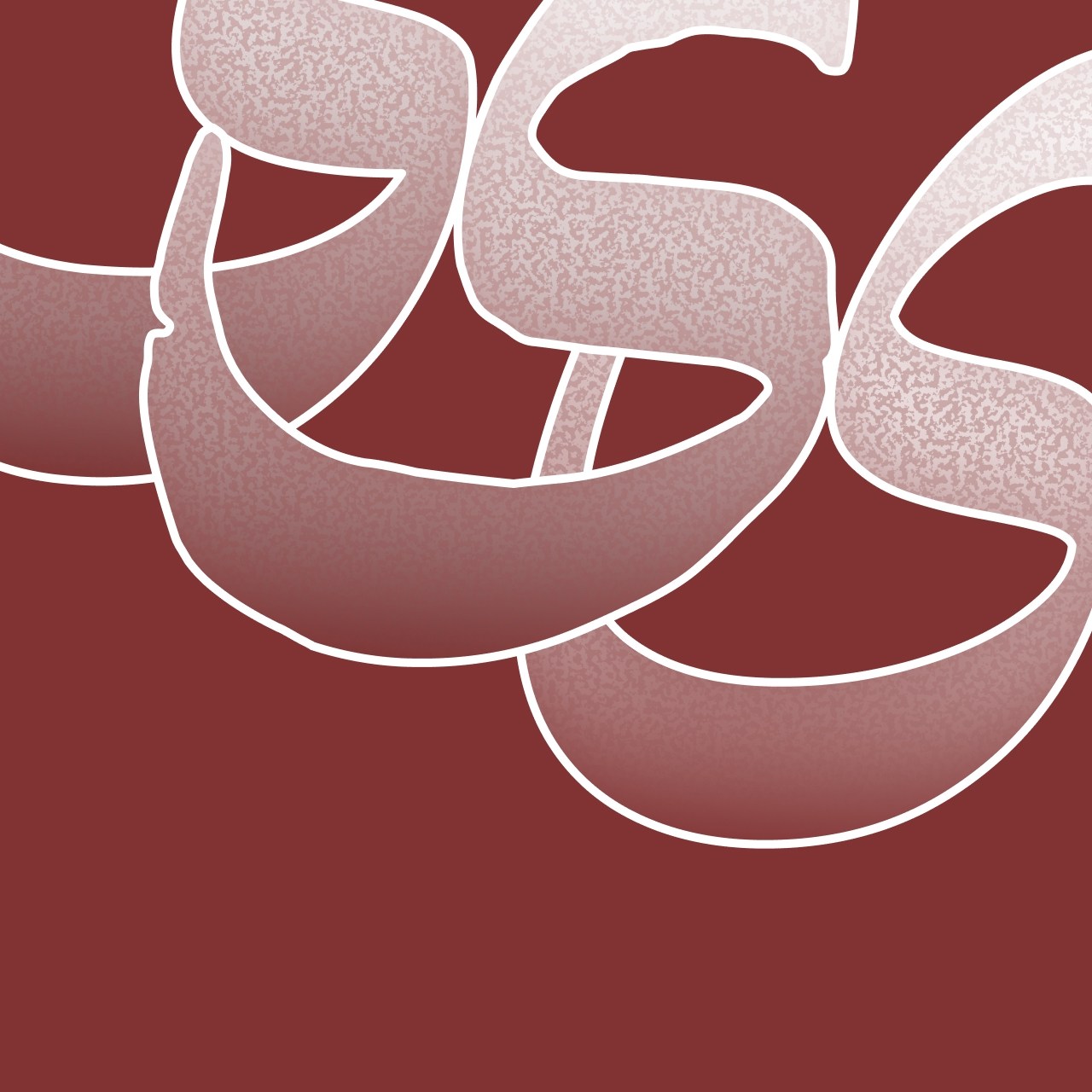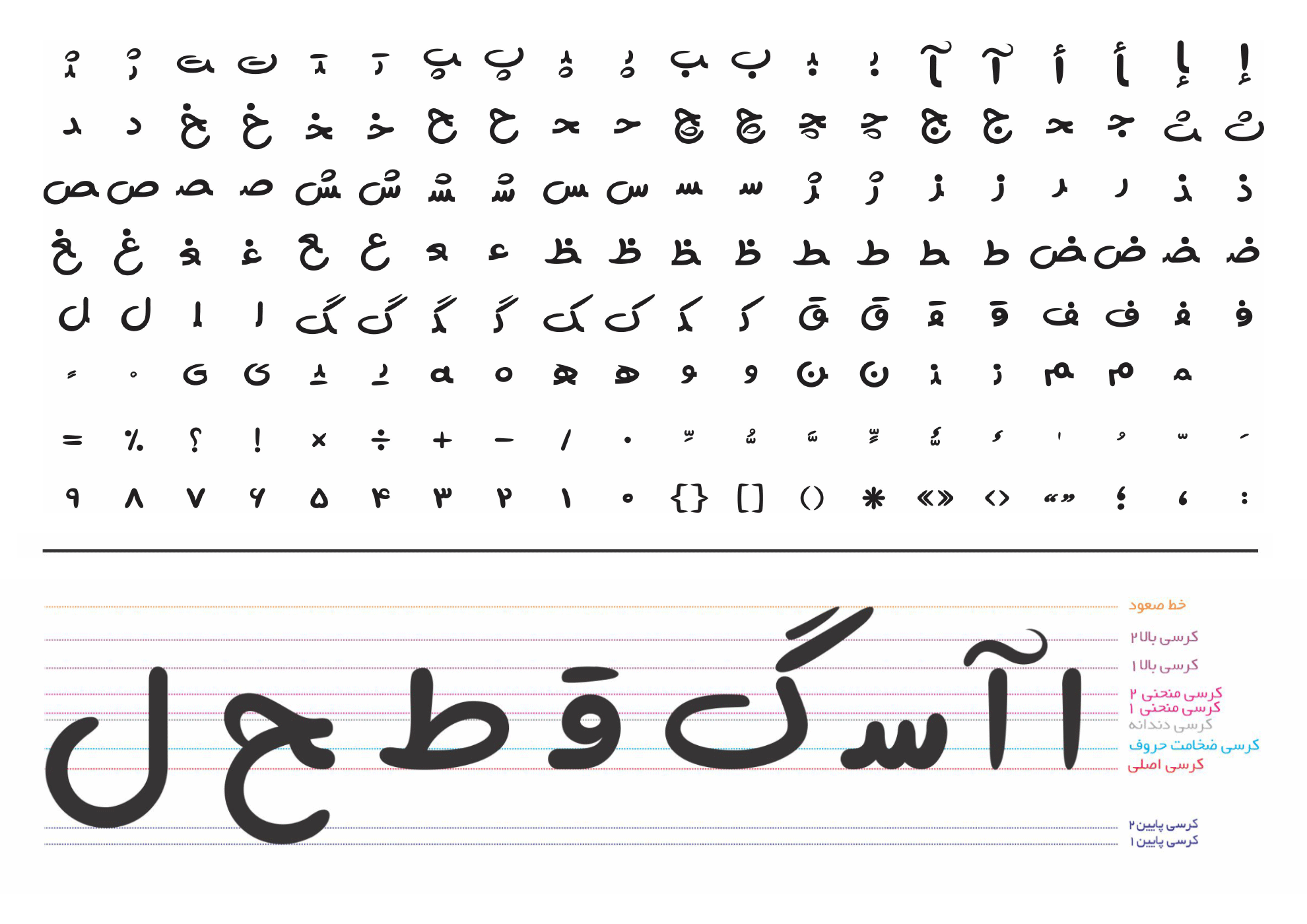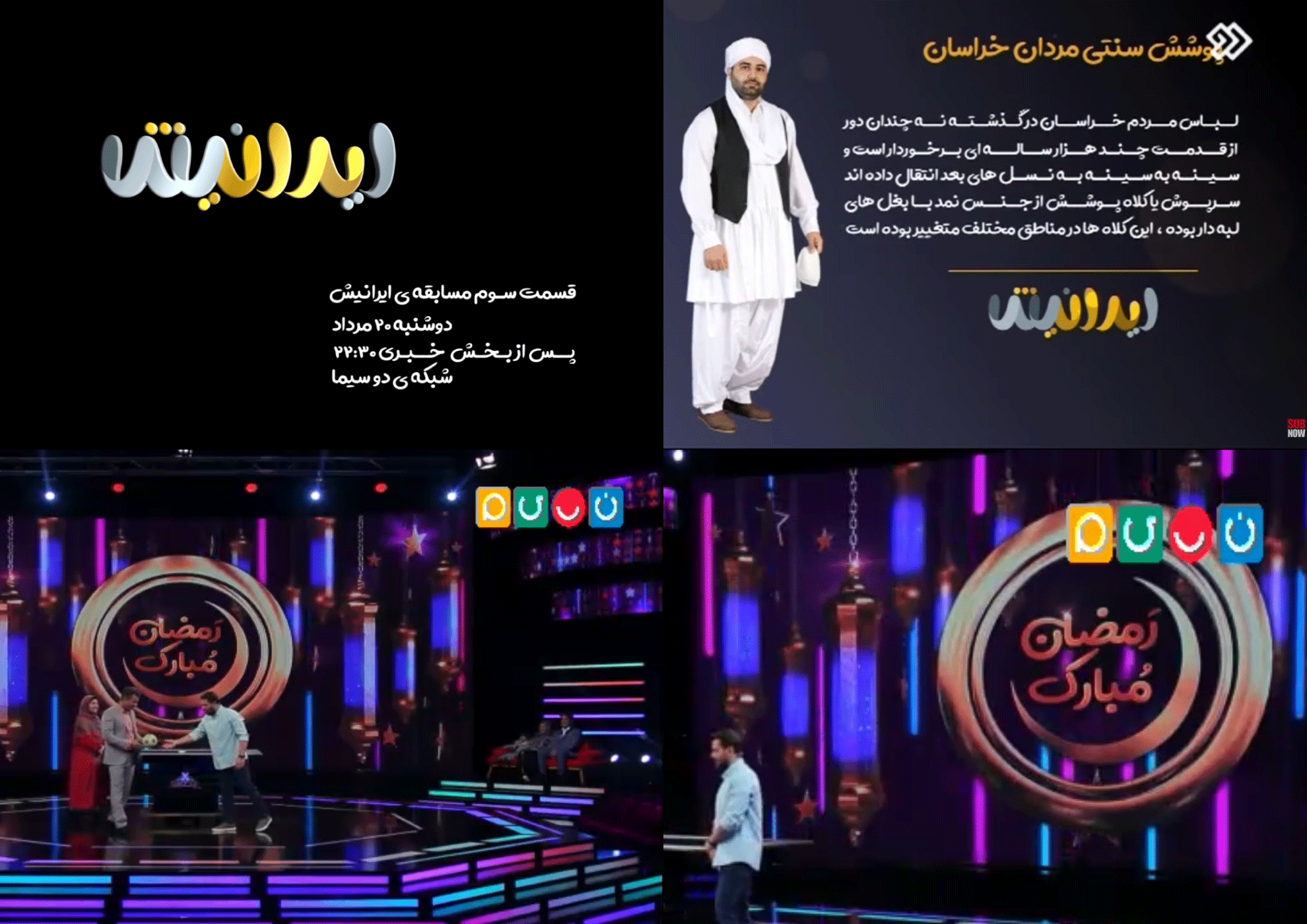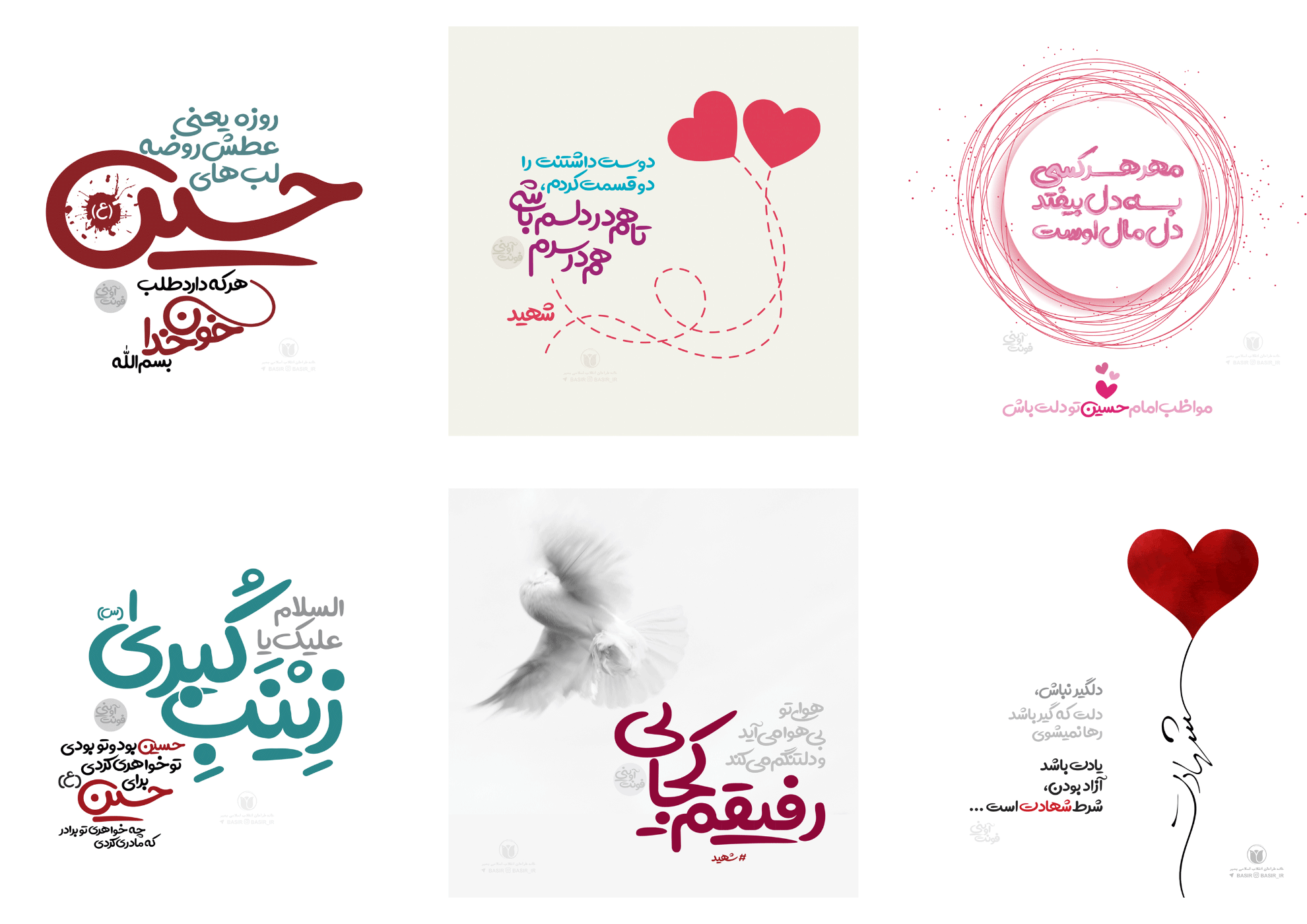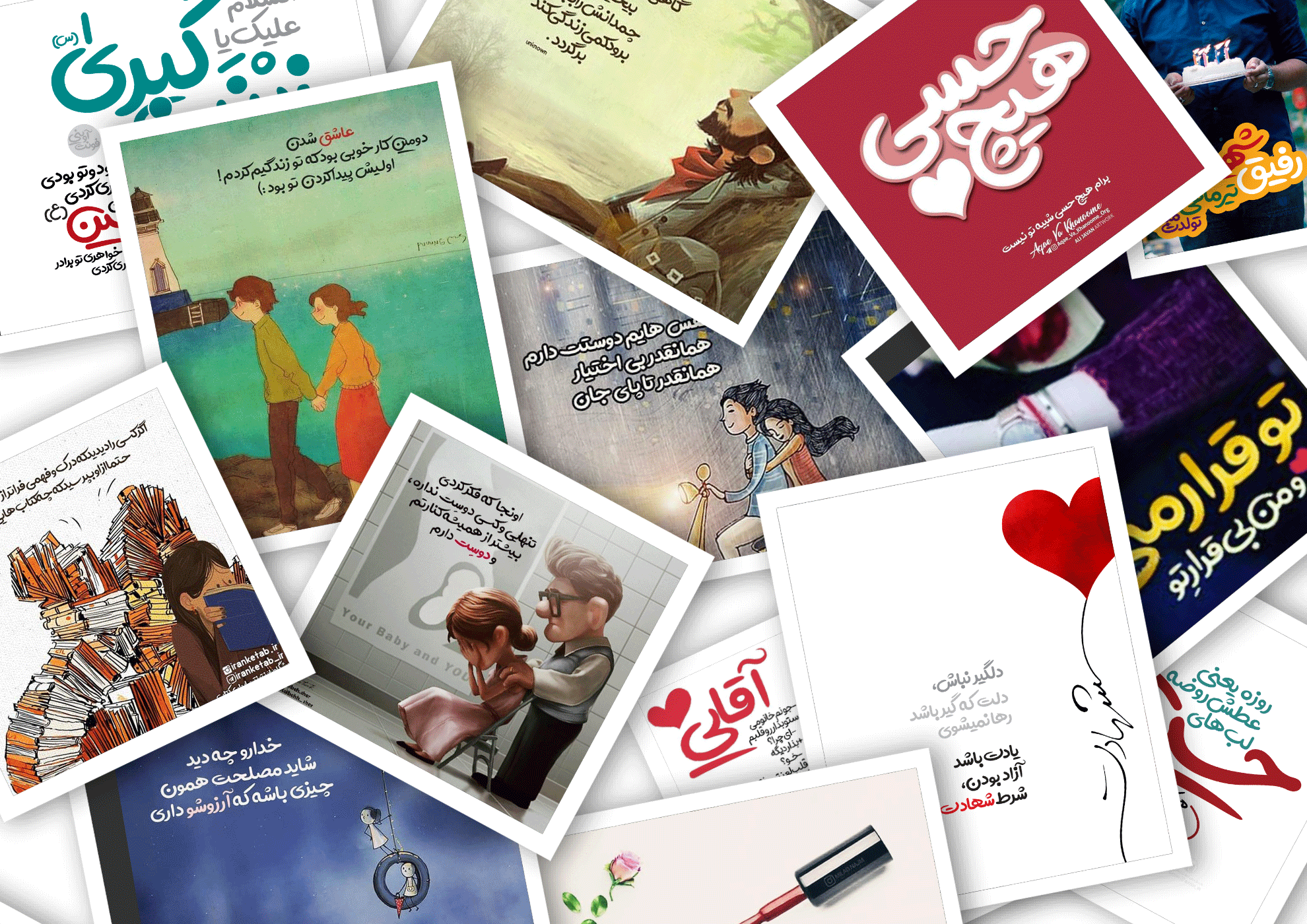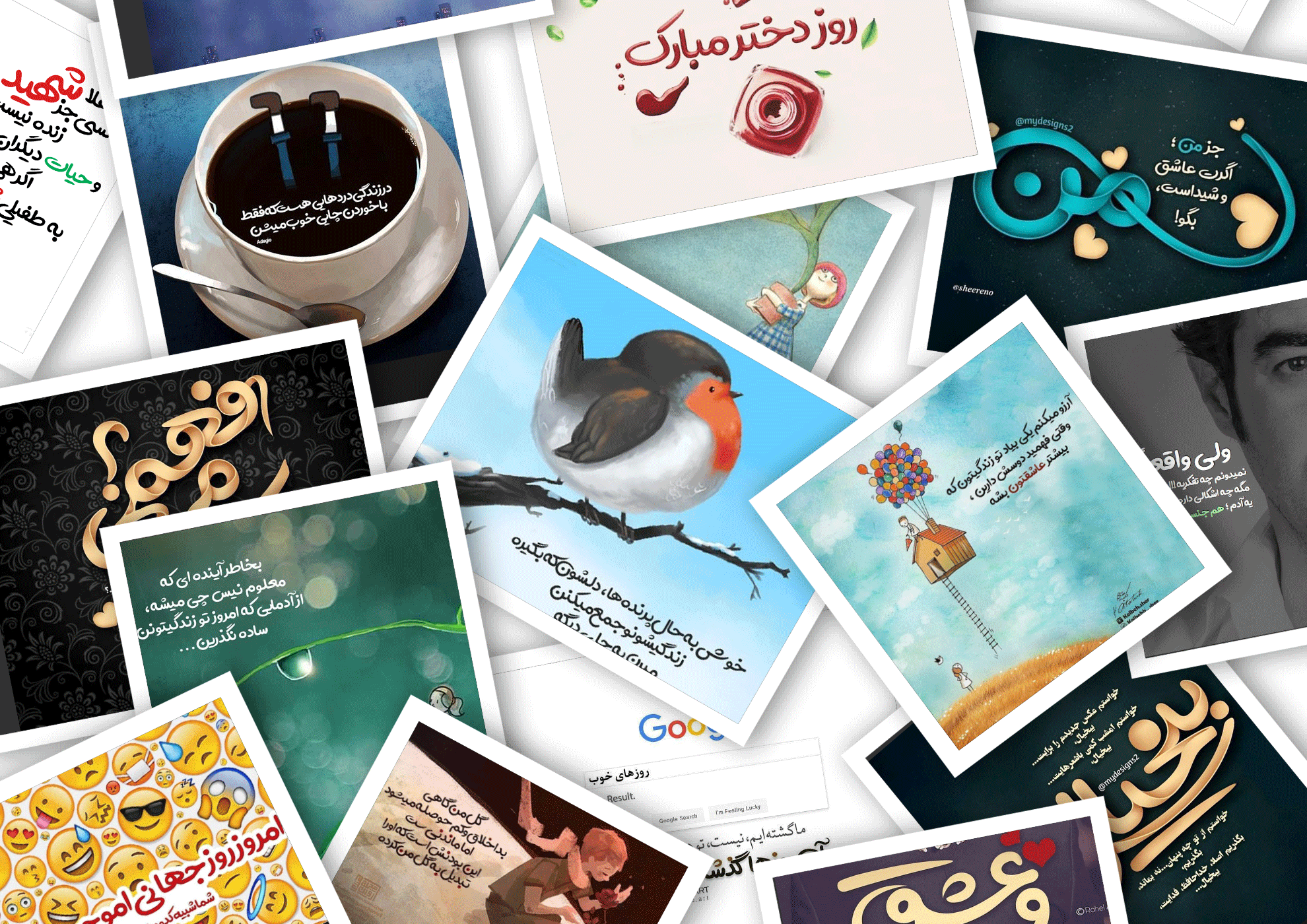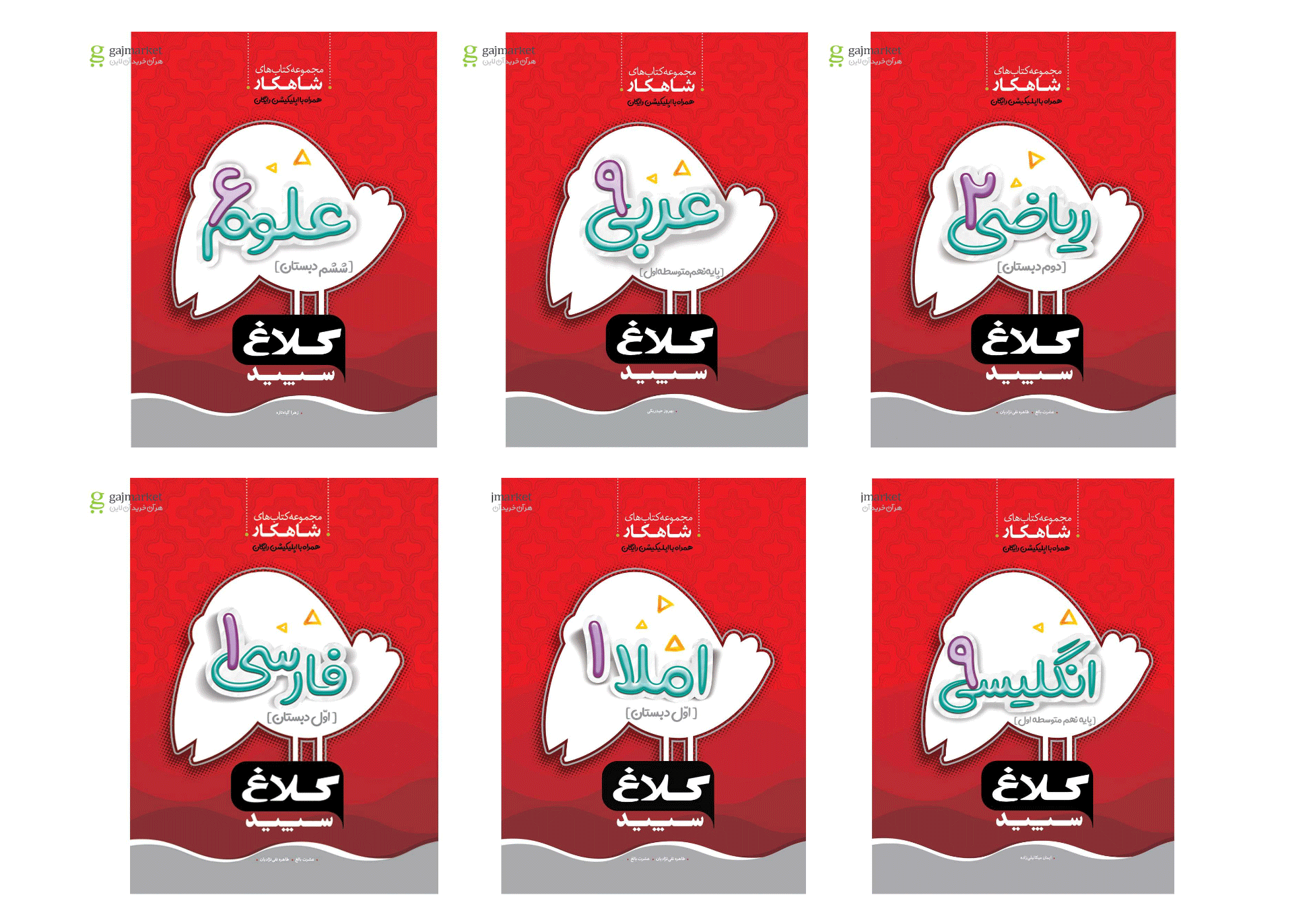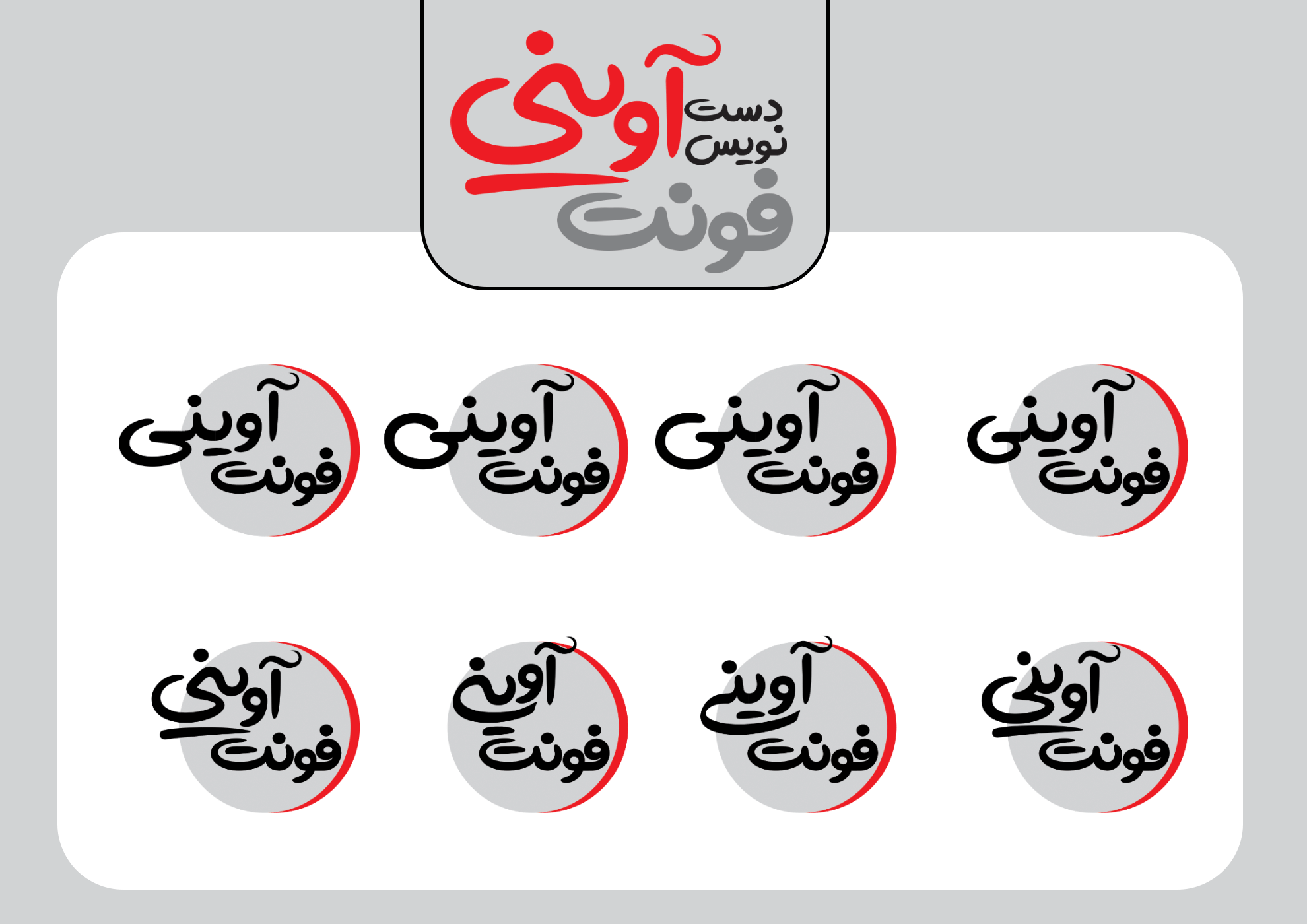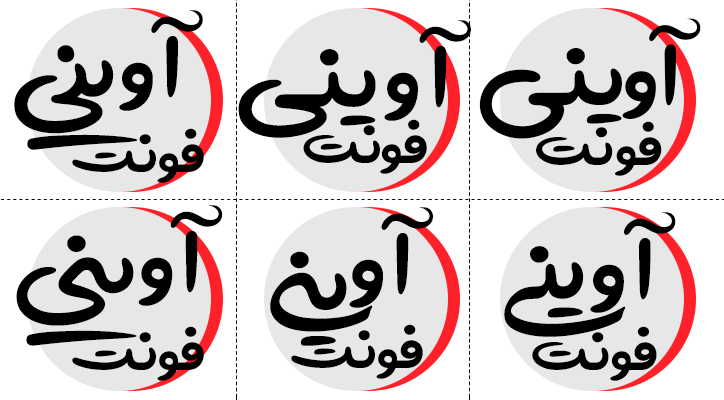
این فونت فقط حاوی حروف فارسی و عربی و انگلیسی است.
در ادامه نمونه متن و کارهای گرافیکی اجرا شده توسط این فونت را ببینید
ترکیبات متغیر و جایگزین کلمه آوینی ( فونت آوینی دارای 800 گلیف ترکیبی و جایگزین می باشد)
نمونه استفاده شده از فونت آوینی در عکس نوشته
نمونه استفاده شده از فونت آوینی در تبلیغات سایت فروشگاهی
نمونه استفاده شده از فونت آوینی در جلد کتاب
نمونه استفاده شده از فونت آوینی در برنامه های صدا و سیما